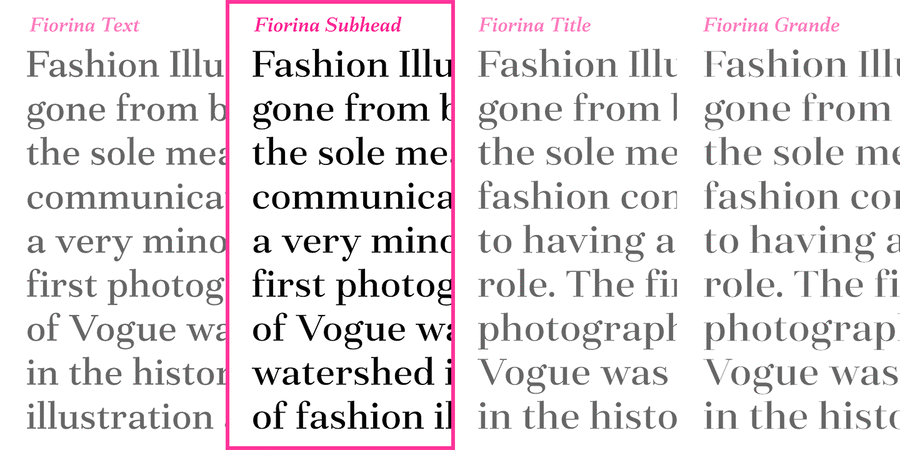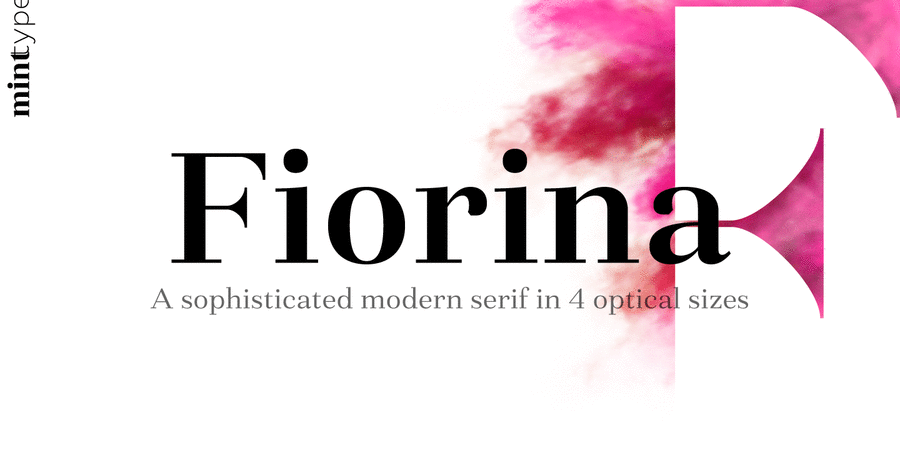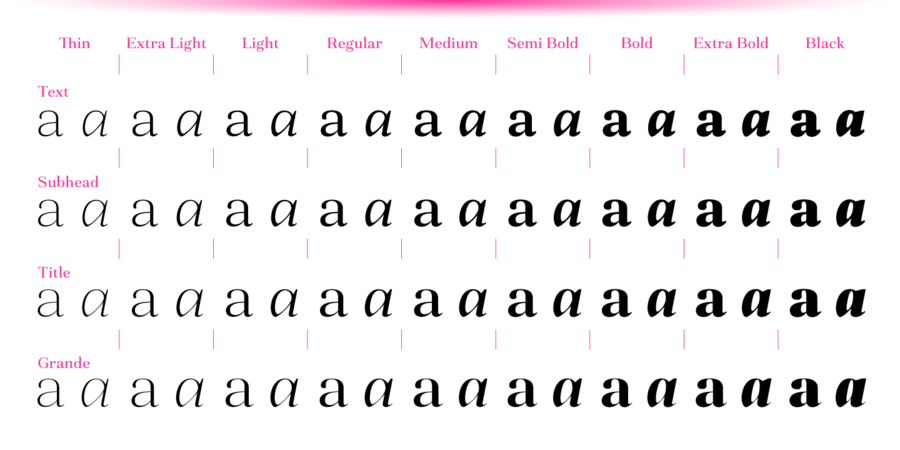
Версія шрифту для підзаголовків. Fiorina – це антиква нового стилю, що складається з 72 накреслень. Шрифт створено в 4 оптичних розмірах: від текстового з помірним контрастом до надконтрастного Grande. Кожен з 4 наборів має 9 насиченостей з відповідним вишуканим курсивом. Загальна різноманітність накреслень робить Fiorina ідеальною гарнітурою для журналів. Набір ґліфів підтримує всі європейські мови на основі латинки, а також усіма основними мовами, в яких використовується кирилиця. Шрифтове сімейство також підтримує численні функції OpenType, включно з 6 наборами цифр, капітеллю, дробами, надрядковими й підрядковими індексами, порядковими числами й багатьма іншими можливостями. Шрифт розробив Андрій Константинов у студії Mint Type у 2020 році.
Асоціації з сімейством шрифтів Fiorina SubheadОсобистість і характер гарнітури:
тонкий, легкий, делікатний, рівний, гармонійний, технічний, сучасний, статичний, культурний, освічений, твердий, чіткий, різкий, гострий, розкішний, гламурний, модний, ювелірний, художній, багатий, дорогий, добірний, елітний, вишуканий, худий, динамічний, серйозний, ефектний, якісний, міський, витончений, прохолодний, свіжий, благородний, красивий, елегантний, майстерний, естетичний, знаменитий, дорогоцінний, комільфо, романтичний, ввічливий, тактичний, формальний, стабільний, солідний, стійкий, переконливий, класичний, інтелігентний, аристократичний, салонний, урочистий, дзвінкий, музичний, прекрасний, блискучий, глянцевий, гордий, срібний, сріблястий, театральний, творчий, виразний, мотивуючий, відповідальний, яскравий, авторитетний, значний, важкий, щільний, помітний, активний
Місто, дизайн, косметика, краса, АСМР, розкіш, преміум, люкс, література, парфумерія, туалетна вода, мода, готель, шоколад, прикраса, ювелір, срібло, коштовності, сервіровка, музика, ресторан, театр, годинник, комільфо, десерт, квіти, бутік, гламур, Інстаграм, культура, парфуми, золото, кохання, романтика, костюм, взуття, одяг, опера, музей, вино, перукарня, пейзаж, Трофей, нагорода Гарнітура має ознаки стилів: